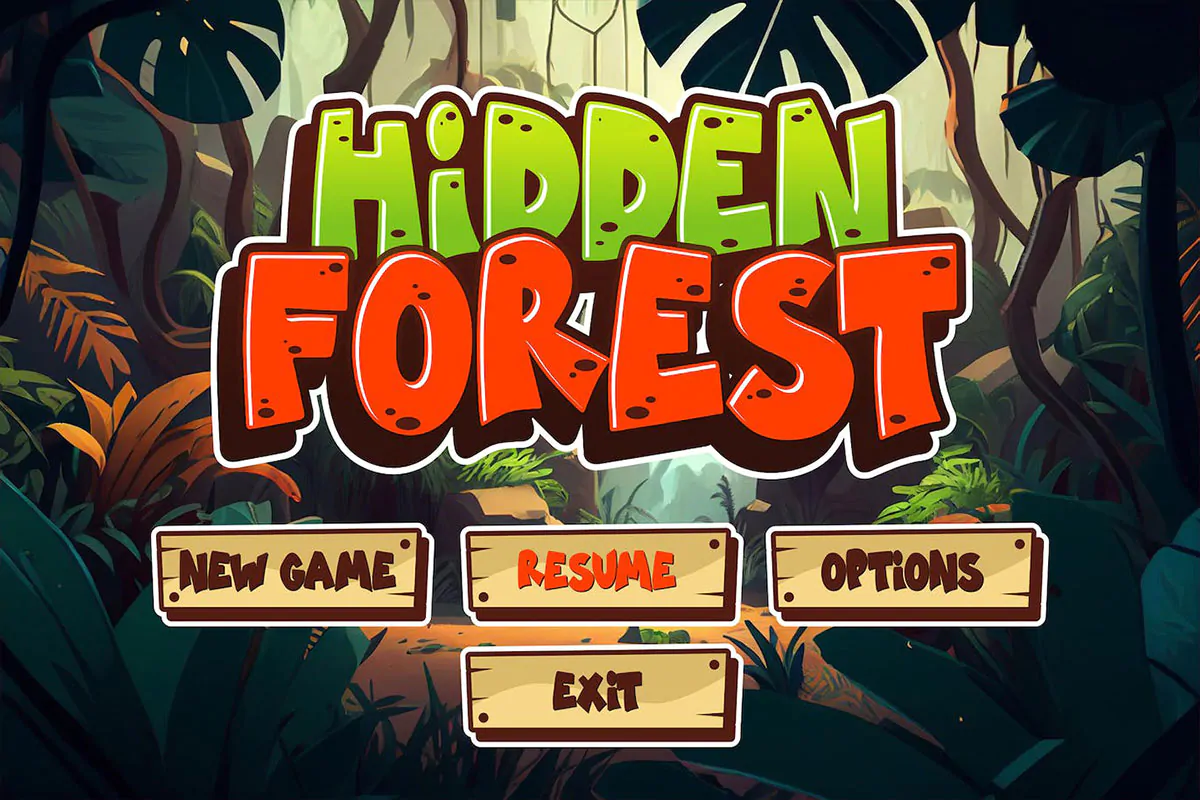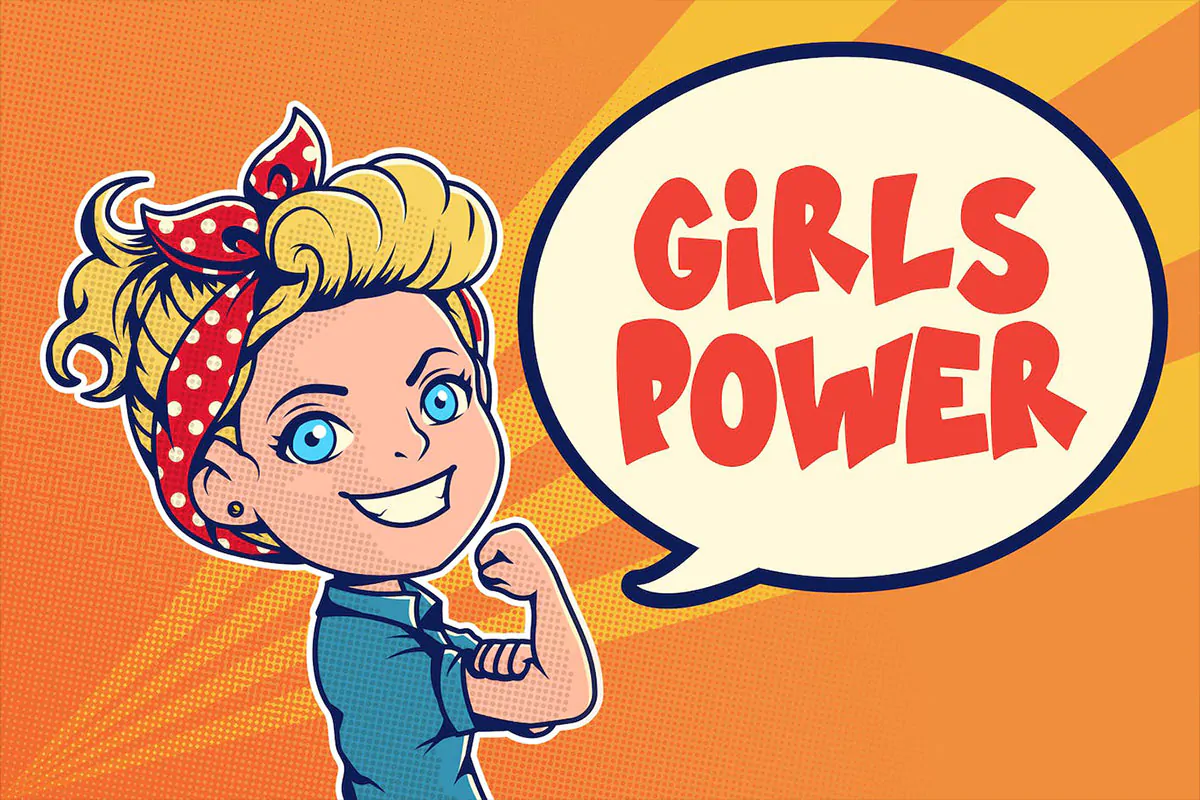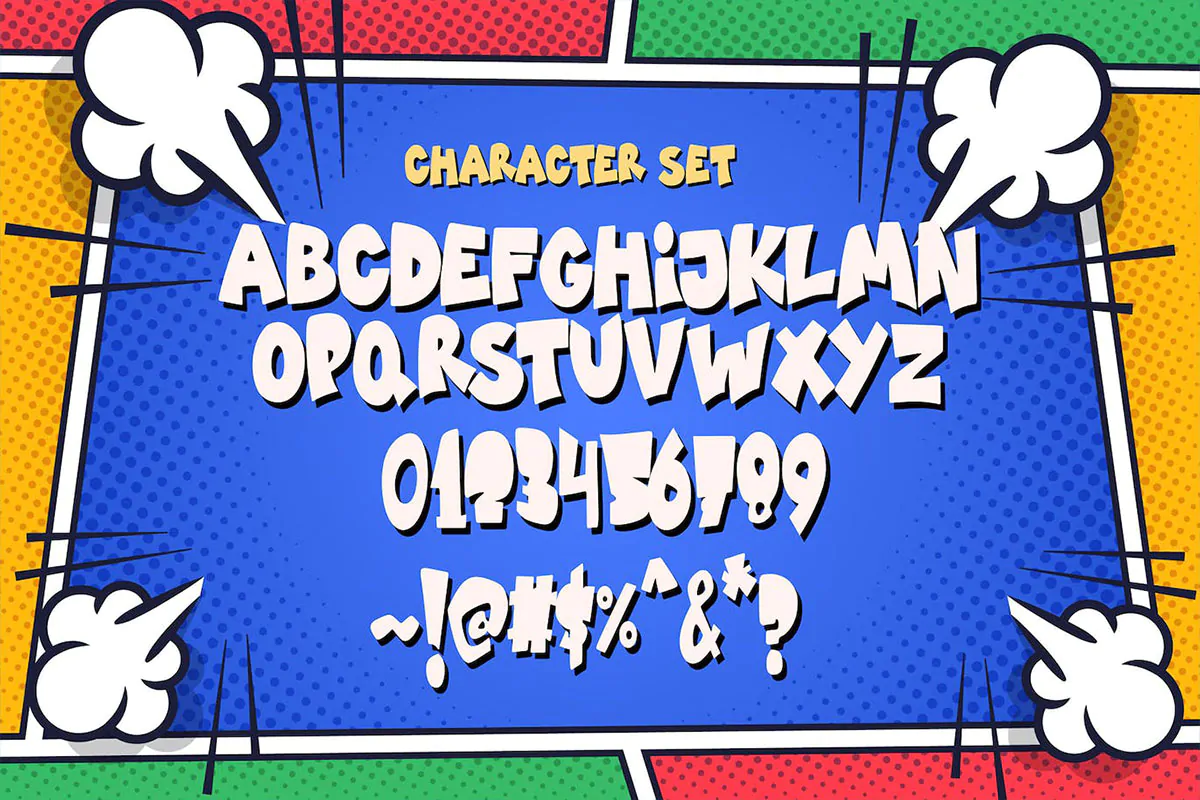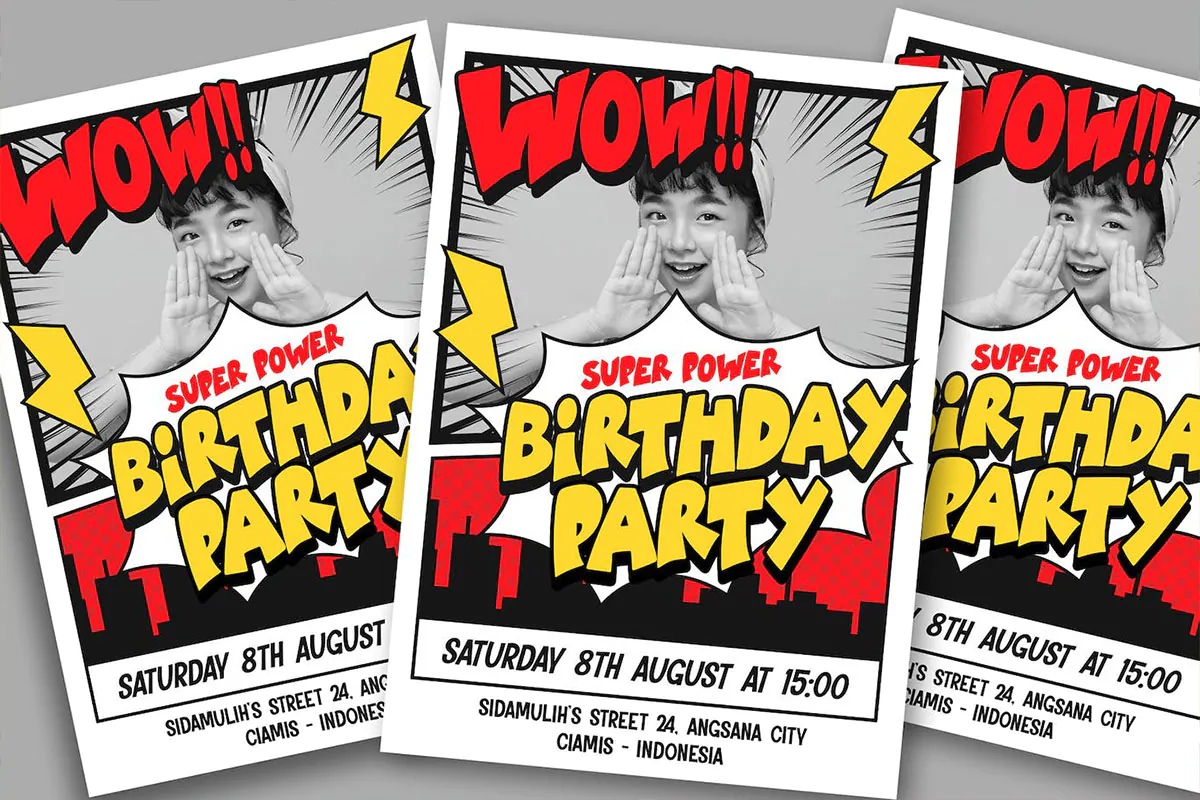
فونت کمیک Boldie Chunks
فونت کمیک انگلیسی
فونت کمیک Boldie Chunks یک قلم فوق العاده انگلیسی است که مناسب برای استفاده در طرح و پروژههای گرافیکی مختلف همچون طراحی انواع پوستر، تراکت، کارت ویزیت، بسته بندی محصولات و … میباشد.